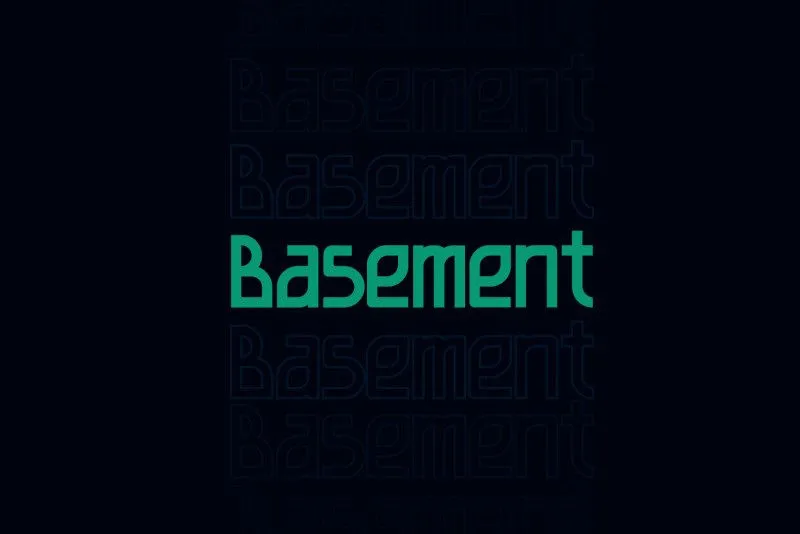
Basement Typeface
Basement é uma tipografia sans-serif criada para headlines. Seu design único foi projetado especificamente para headlines, garantindo que sua mensagem seja imediatamente visível e atrativa. Ideal para criar um impacto forte em qualquer documento ou tela, esta fonte é gratuita para uso pessoal. Desenvolvida pelo designer Armando Nhabanga, Basement traz uma proposta inovadora ao mundo das fonts sans-serif. Que tal experimentar essa novidade em suas próximas criações visuais? Esperamos que você se divirta com seu design original e versátil.
Designer: Armando Nhabanga